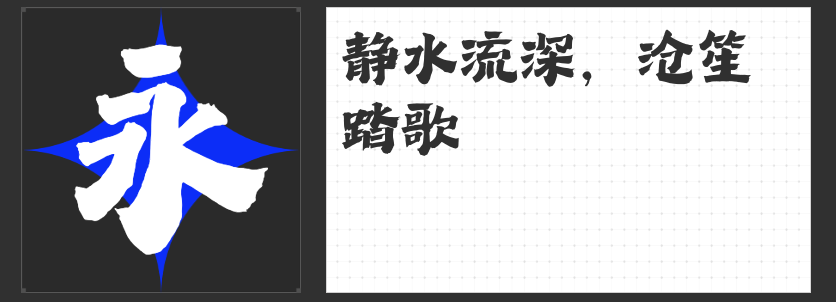
设计中的字库字体精选:打造视觉盛宴的四大瑰宝
在设计的广阔世界中,字体不仅是信息的载体,更是情感和风格的传递者。今天,我们就来探索四款专为设计而生的字库字体,它们各具特色,能够为你的作品增添无限魅力。
1.造字侠热辣隶简
这款字体融合了传统隶书与现代设计的精髓,呈现出一种庄重而不失活力的视觉效果。其结构稳定、中宫扁宽,笔画线条简洁明快,既保留了隶书的历史韵味,又注入了现代气息。无论是国潮设计、教育宣传、文化产品包装,还是海报制作、品牌塑造,造字侠热辣隶简都能成为你的得力助手,让你的作品在众多设计中脱颖而出。
这款字体以其方正的结构和均衡的视觉效果,成为设计界的宠儿。其笔画横平竖直,棱角分明,展现出简约而不失力量的美感。励字开拓者系列共五款字体,能够轻松实现从正文到标题的平滑过渡,满足各种设计场景的需求。更令人惊喜的是,这款字体还包含了众多网红流行用字,让你的设计更加贴近潮流。
这款字体以其自由率真、活泼灵动的风格,深受设计师们的喜爱。其单字结构周正而不失松弛,笔画圆润且粗细过渡自然,给人一种轻松愉悦的感觉。无论是用于广告设计、包装制作,还是插画配文、社交媒体发布,造字侠醉春风简繁都能为你的作品增添一份独特的韵味。
4.万人字造踏歌行体
这款字体以其方整严谨的结构和动感十足的笔画布局,成为设计领域的又一佳作。其用笔方整中带着圆润,笔力劲健,仿佛蓄势待发。整体单字笔画带有古法用笔的感觉,增强了整体风格特征。无论是用于标志设计、书籍装帧,还是展览展示、广告招牌,万人字造踏歌行体都能让你的作品焕发出别样的光彩。